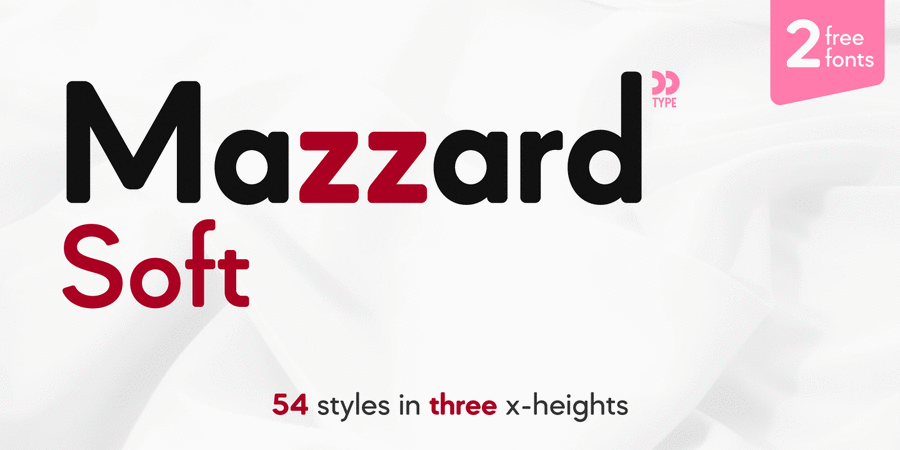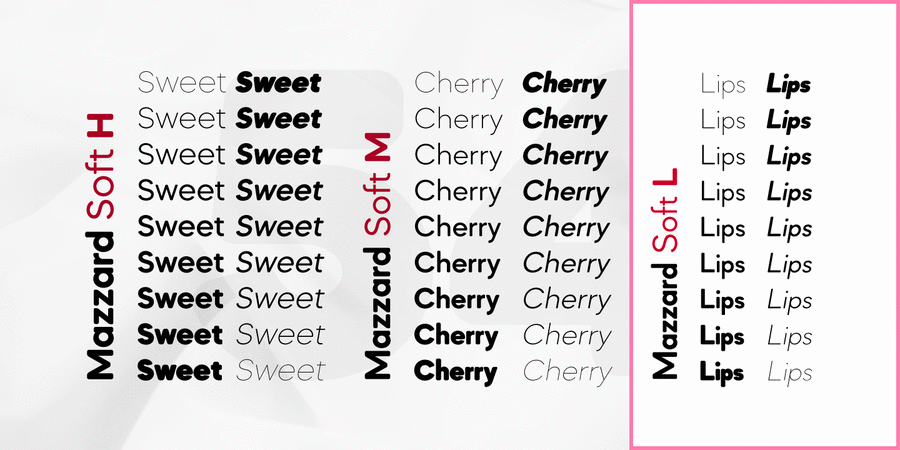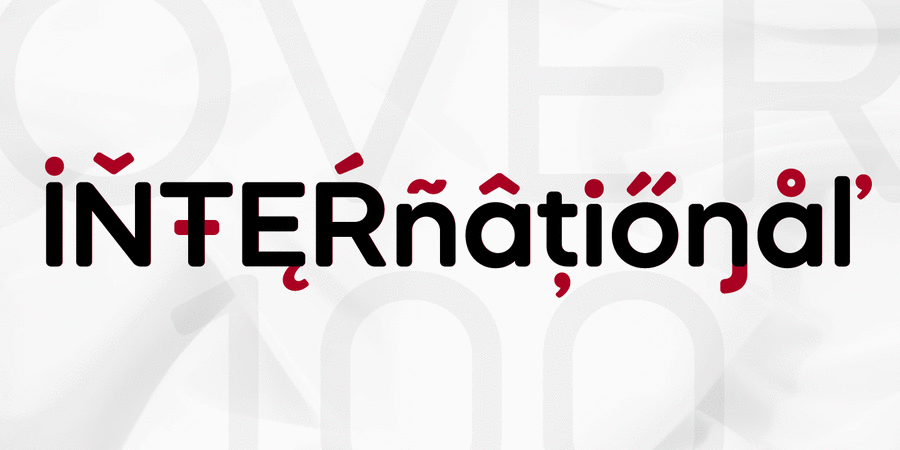
Mazzard Soft L – це частина шрифтового сімейства Mazzard Soft, котре є версією з заокругленими кутами суперсімейства Mazzard. У цій версії є ще два геометричних гротеска, які різняться висотою рядкових знаків (M і H).
Шрифт має широкий спектр підтримки мов, зокрема кирилицю, та пропонує великій вибір альтернативних гліфів.
Шрифт розробив Олег Ліщук в 2019 році.
Асоціації з сімейством шрифтів Mazzard Soft LОсобистість і характер гарнітури:
точний, рівний, статичний, стійкий, штучний, міський, чистий, тонкий, дротяний, легкий, прохолодний, ясний, невагомий, прозорий, крихкий, модний, приємний, худий, неоновий, доброзичливий, добродушний, добрий, грайливий, круглий, М'який, комфортний, свіжий, симпатичний, пластмасовий, гладенький, мирний, урбаністичний, позитивний, якісний, популярний, зрозумілий, впевнений, сильний, переконливий, важливий, мотивуючий, залізничний, амбітний, яскравий, помітний, активний, привітний, милий, дитячий, наївний, смачний, щедрий, пишний, затишний, сімейний, домашній, потужний, важкий, щільний, тісний, гучний, сміливий, гумовий
— Гарнітура асоціюється з віком: